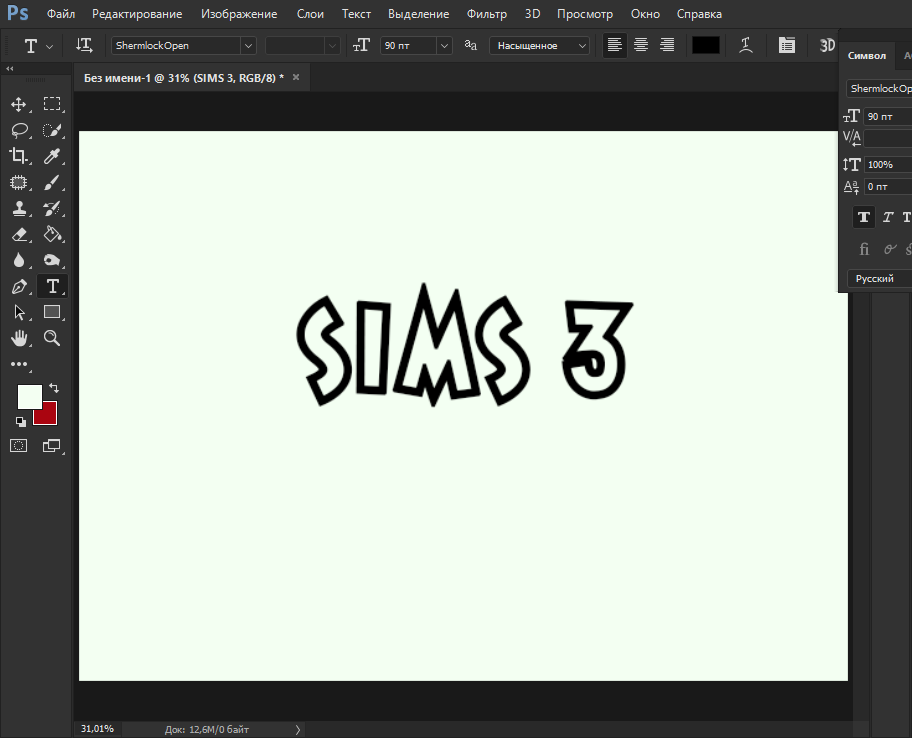
Шрифт из игры Симс 3 для фотошопа
Чего-то не встречал ни в одной части похожего шрифта. Самую малость лого напоминает и только. Более адекватный шрифт из лого, если кому нужно. Кириллицы нет, если что.